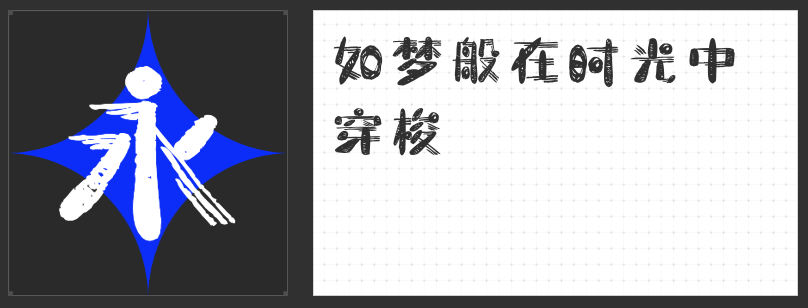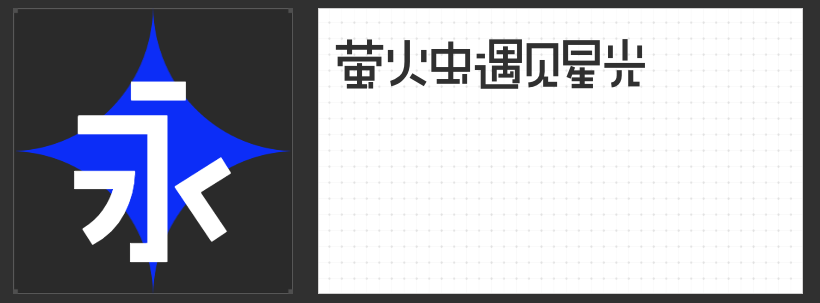
动漫与二次元设计字体精选:四款不可错过的创意字库
在动漫与二次元设计的世界里,字体不仅是传递信息的工具,更是塑造风格、营造氛围的关键元素。今天,我们为大家精选了四款专为动漫、二次元设计而生的创意字库字体,它们各具特色,能够满足你多样化的设计需求。
这款硬笔手写字体的名字源自《西游记》中玉皇大帝的居所——灵霄宝殿,其笔画硬挺利落,字形古风劲萧,饱满均匀,结构布局沉稳,笔力劲健。无论是仙侠题材的海报标题,还是网游世界的宣传标语,造字侠灵霄简繁 传神都能以其独特的韵味,瞬间抓住观众的眼球,引领他们进入一个充满奇幻与神秘的世界。
2.字恋狂白日梦简
这款字体以其凌乱的线条笔画,仿佛带着做梦般的迷离感,穿梭在时光的长河中。它适用于绘本、漫画等场景,能够为画面增添一抹梦幻与浪漫的色彩。字恋狂白日梦简的每一笔每一划都仿佛在诉说着一个关于梦想与幻想的故事,让你的作品更加引人入胜。
3.字恋狂澄空 迟风
这款以手写感为基础的字体,字型上松下紧,重心略低,结构灵活多变。字面根据每个字的不同结构而发生变化,更显灵活有趣。字间距安排合理得当,组合起来富有节奏感,使得整体设计更加和谐统一。部分字体的偏旁与部首字面占比差距大,单字结构变化丰富,为设计增添了更多的可能性。笔画粗细均匀,设计简洁,流畅饱满的弧线与利落的直线相融合,部分笔画折笔处运用平直切角的处理方式,减少了锐度,使得整体更加柔和。笔画之间根据空间和位置采用了“断开”的处理方式,增加了轻快感,让设计更加生动自然。
4.字恋狂灵珑简
这款融合手写感的创意体,以其另类的横细竖粗、稚嫩的笔触,模仿不规则的填涂方式,再加上圆点的点缀,使得整体结构显得肥胖而天真。字恋狂灵珑简适用于各种充满童趣与幻想的动漫、二次元设计,能够为你的作品增添一抹独特的魅力。
以上四款字体各具特色,无论是想要营造古风仙侠的氛围,还是追求梦幻浪漫的感觉,或是需要灵活多变的设计元素,或是想要展现童趣与幻想,它们都能满足你的需求。快来尝试这些字体,为你的动漫与二次元设计作品增添更多的创意与色彩吧!